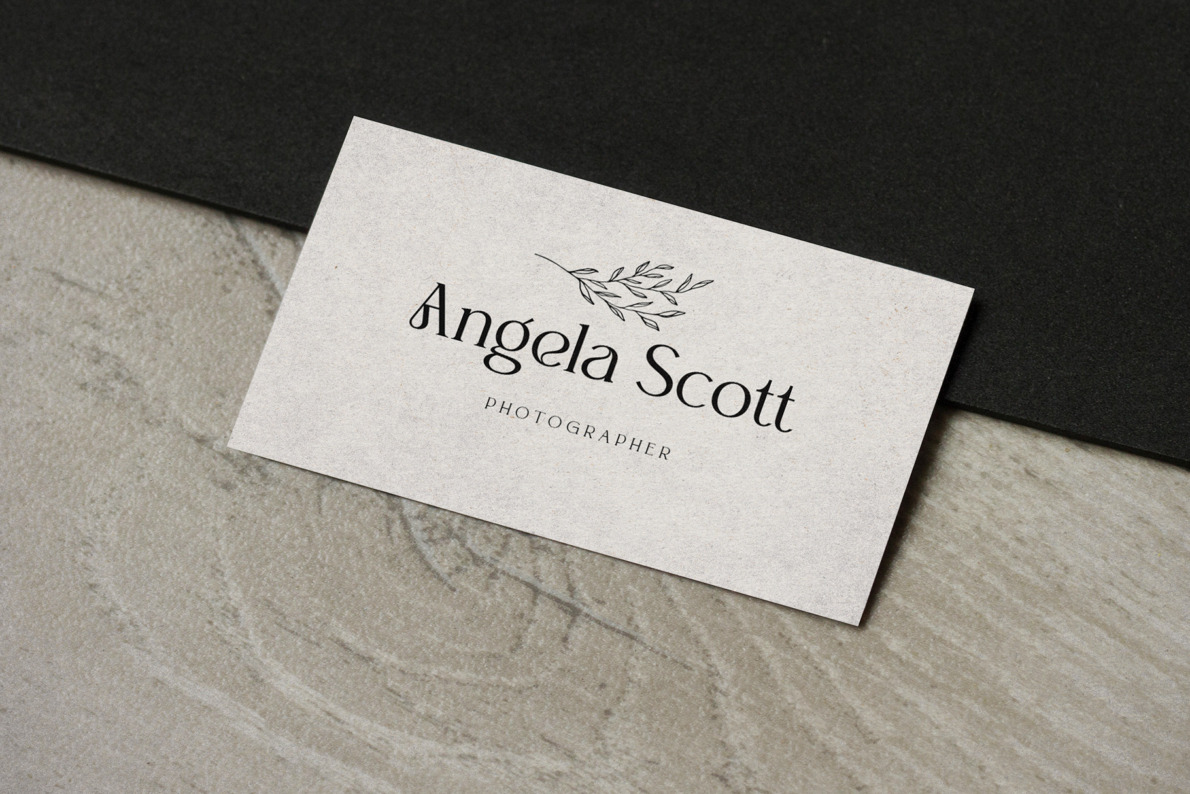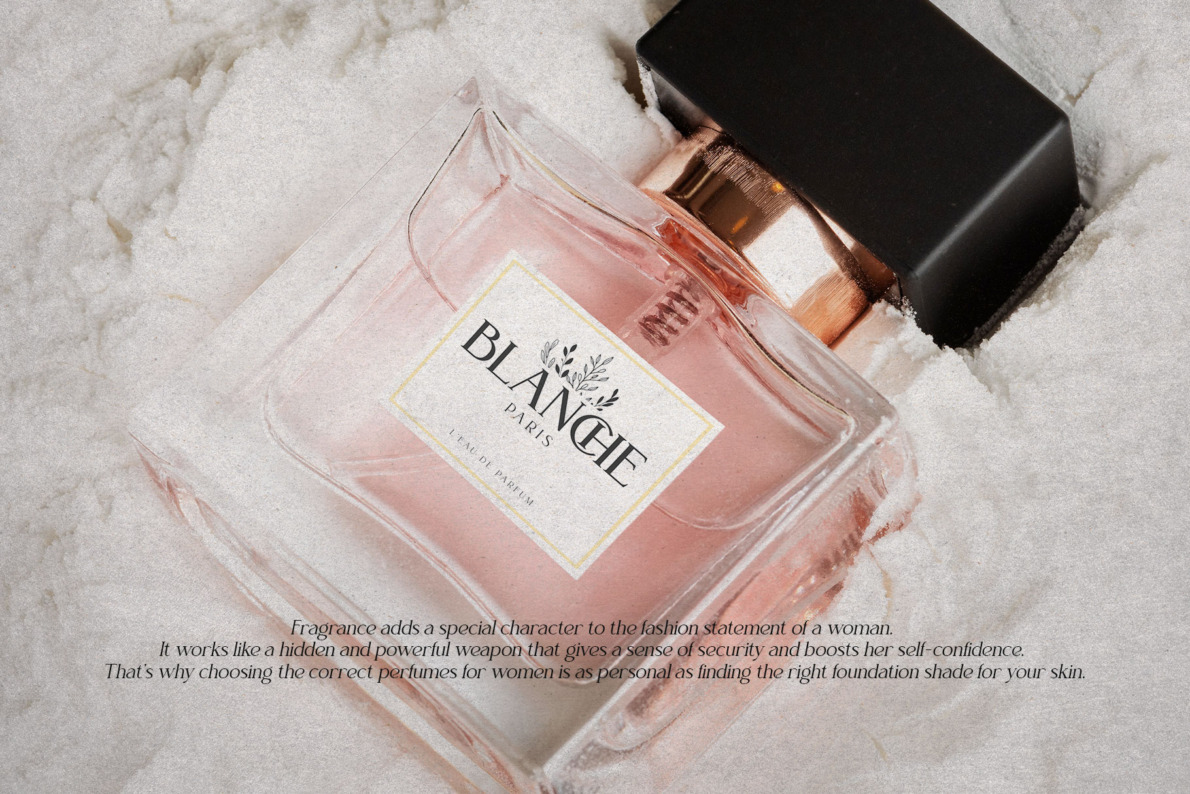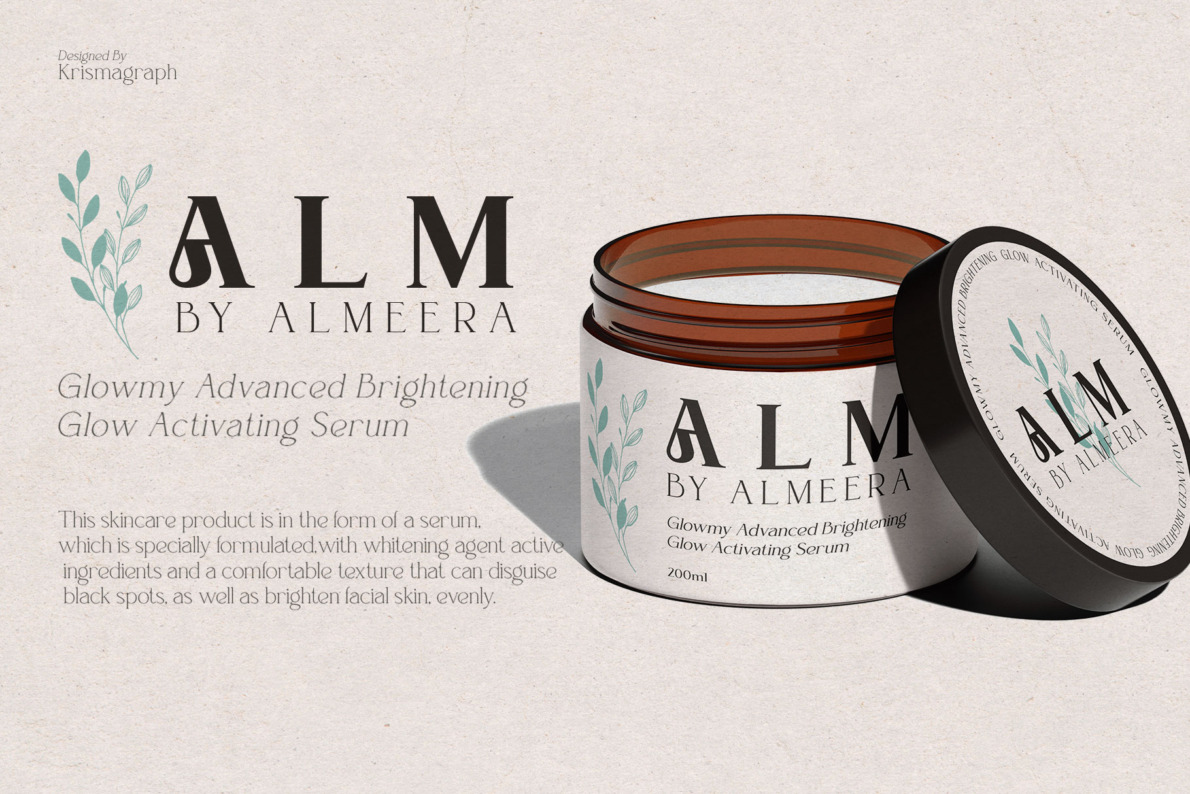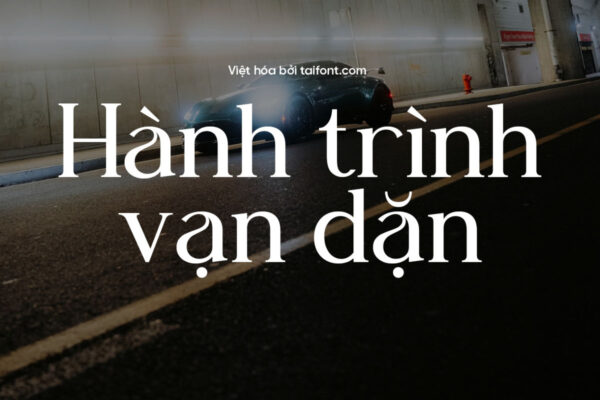
Giới thiệu về Font TF Glamoure Everyday Việt hóa
TF Glamoure Everyday Việt hóa là một font chữ có chân (serif) nổi bật với vẻ đẹp nữ tính, tinh tế và đầy quyến rũ. Với những đường nét được thiết kế mềm mại, duyên dáng và thanh lịch, font này toát lên phong thái sang trọng và hiện đại, rất phù hợp để tạo nên sự độc đáo và cuốn hút cho các thiết kế dành riêng cho phái đẹp.
Với sự mềm mại và tính thẩm mỹ cao, Glamoure Everyday là lựa chọn lý tưởng cho các ấn phẩm cần truyền tải vẻ đẹp, phong cách và sự tinh tế, đặc biệt là:
- Thiết kế mỹ phẩm: Hoàn hảo để sử dụng trên bao bì sản phẩm, catalogue, hoặc các chiến dịch marketing. Font này giúp khẳng định chất lượng, sự sang trọng và vẻ đẹp tự nhiên của thương hiệu mỹ phẩm, thu hút ánh nhìn của khách hàng.
- Thiết kế thời trang: Lý tưởng cho các thương hiệu thời trang nữ, từ nhãn mác sản phẩm, lookbook, đến các chiến dịch quảng bá bộ sưu tập. Font này giúp truyền tải sự thanh lịch, quyến rũ và tinh tế của trang phục, nâng tầm giá trị thương hiệu.
- Name card (Danh thiếp): Phù hợp để sử dụng trên danh thiếp cá nhân hoặc doanh nghiệp, đặc biệt là trong các ngành nghề liên quan đến làm đẹp, thời trang, hoặc các dịch vụ cao cấp. Font này sẽ giúp danh thiếp của bạn trở nên chuyên nghiệp, sang trọng và để lại ấn tượng về sự tinh tế.
Với TF Glamoure Everyday Việt hóa, bạn có thể dễ dàng thổi hồn nữ tính và sự sang trọng vào các thiết kế, tạo ra những sản phẩm không chỉ đẹp mắt mà còn đầy cảm xúc và sức hút đặc biệt với phái đẹp.
Font Việt hóa TF Glamoure Everyday